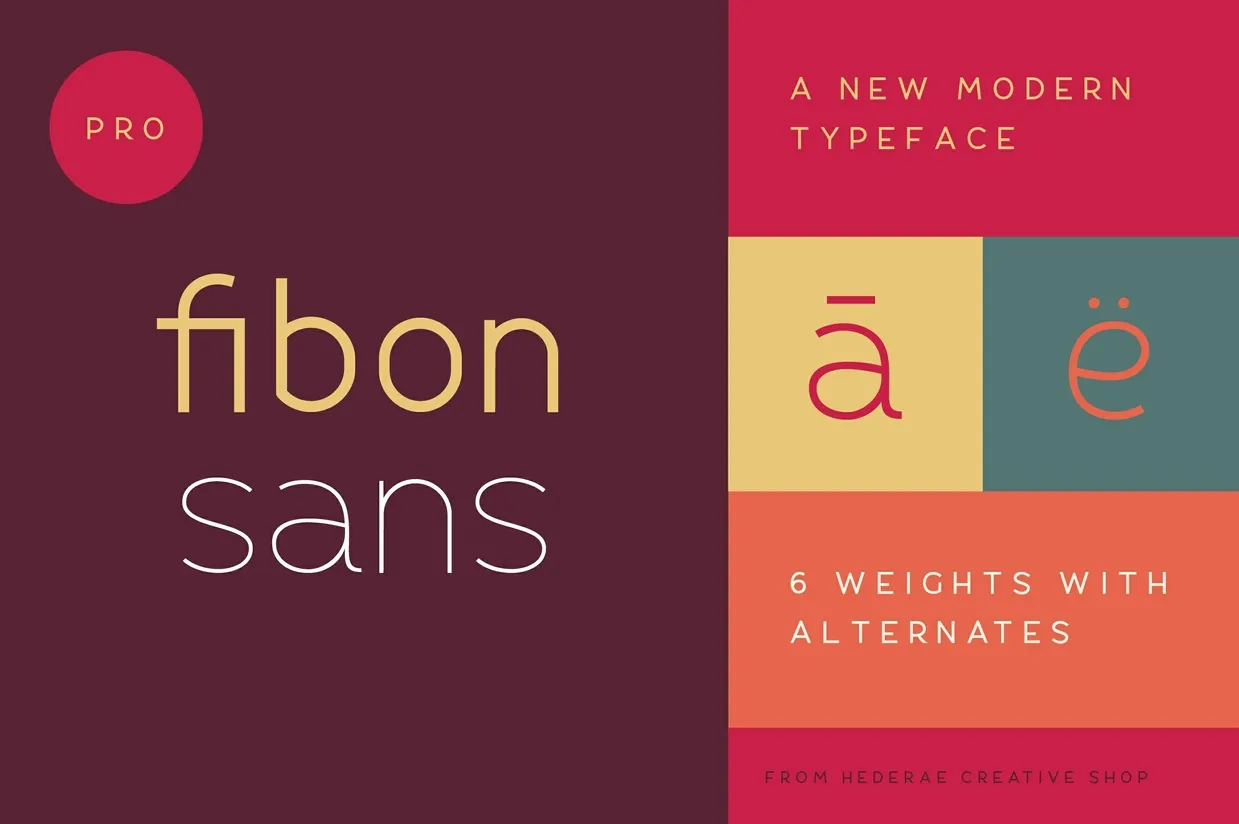
Fibon Sans é uma famosa família de tipo desenvolvida por valeriodelledera que destaca-se pelo equilíbrio entre estilos e contraste baixo, criando um layout geométrico e altamente legível. Esta fonte é particularmente versátil para uso tanto em textos quanto nas aplicações de exibição, onde suas curvas proporcionam movimento dinâmico quando se utiliza para compor texto. Ideal para quem deseja adicionar uma dose moderna às composições, Fibon Sans oferece um toque atraente e elegante que complementa qualquer layout gráfico. É uma escolha excepcional para revistas de moda, logotipos e lojas onde deseja transmitir uma sensação de atemporalidade ao mesmo tempo em que incorpora o ritmo da modernidade. Esta família de tipo OpenType também oferece suporte para idiomas CE, tornando-a versátil para múltiplas aplicações regionais. A fonte inclui ligaturas e adorna a sua oferta de recursos com um brilho moderno e uma textura sofisticada que se destaca ainda mais entre as famílias de tipos existentes. Não hesite em experimentar Fibon Sans para dar vida e personalidade à sua próxima criação, seja ela um design editorial ou visualmente impactante.